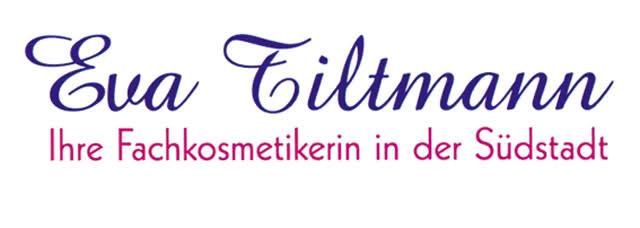
Wer kennt diese 2 Schriftarten?
Hallo, kann mir jemand sagen wie diese 2 Schriftarten heißen? Kenne mich in der Typografie leider nicht gut aus!
die Schreibschrift kenne ich nicht, die Groteske könnte die Kabel sein,
[specimen=Ihre Fachkosmetikeri:9sgz6c1l]23691[/specimen:9sgz6c1l] allerdings mit seltsam niedriger x-Höhe